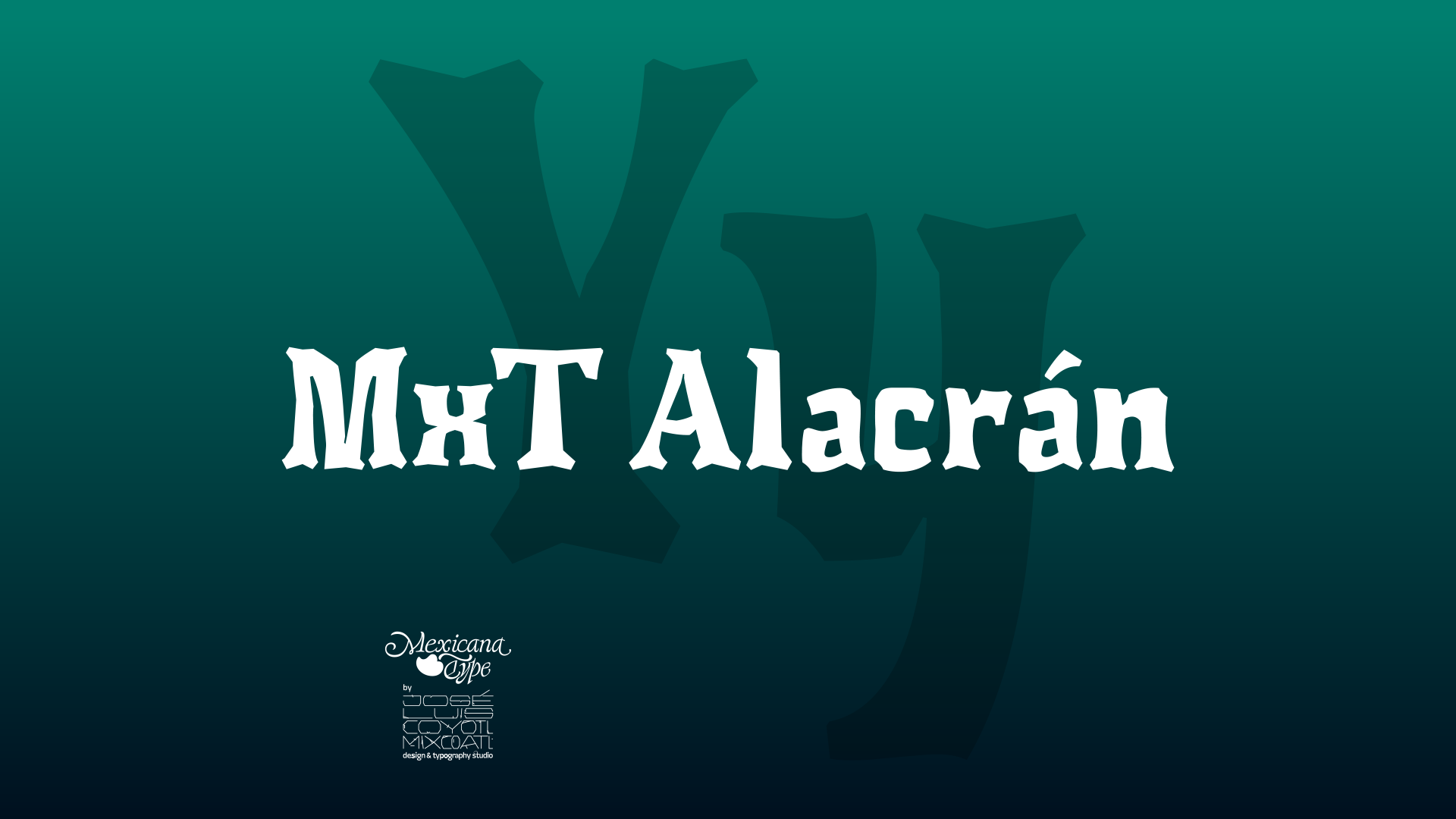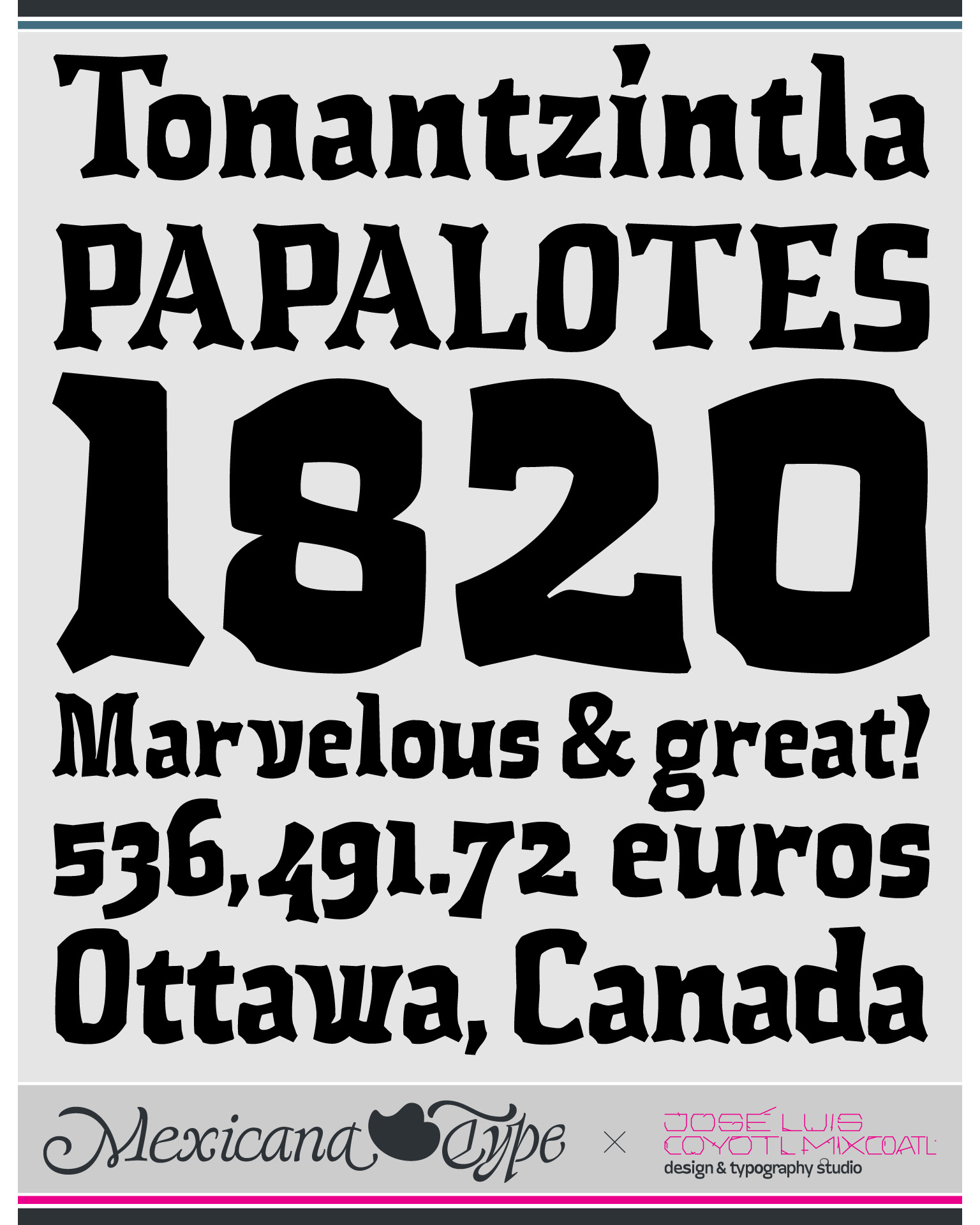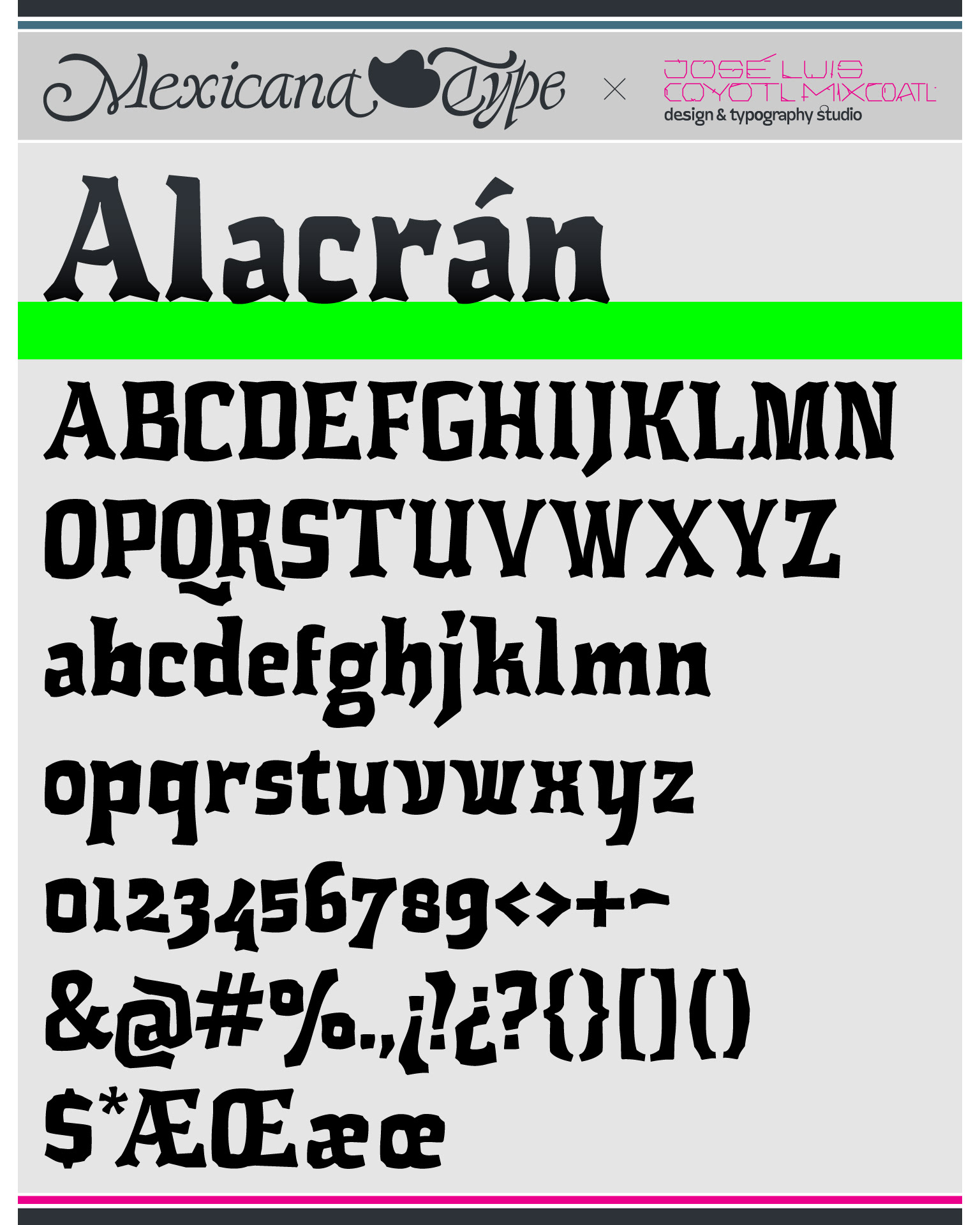
MxT Alacrán está diseñada en base tallados de esculturas de obsidiana, cantera y arquitectura precolombina. Sus cortes rústicos, trazos gruesos y sólidos hacen énfasis en la fortaleza de su estructura, en su apariencia ósea y sugerentes detalles góticos. Su diseño fue pensado en base a cortes en bloque e irregulares, con la intención de generar una textura asimétrica en el texto que generara una sensación de letra antigua sin perder cuerpo, lo suficientemente pesada para títulos preservando su legibilidad.